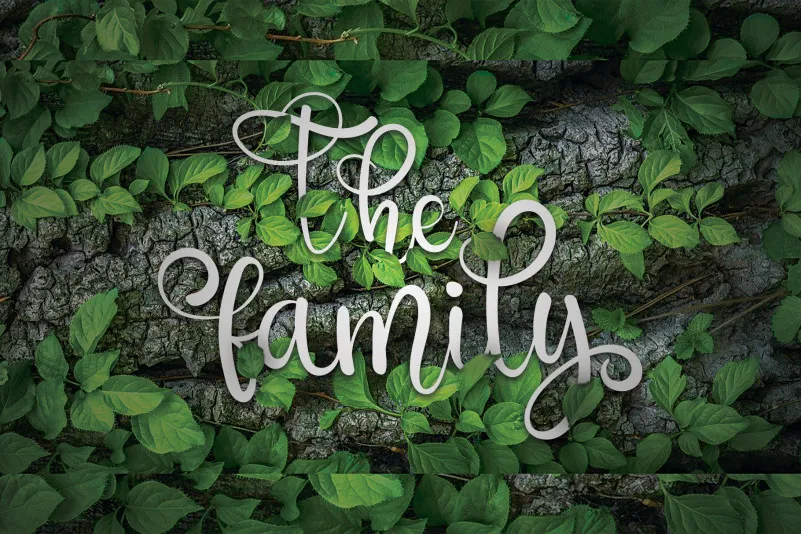
Esta fonte The Family Font é ideal para quem busca um toque romântico e encantador para seus projetos. Ela é uma tipografia de calligrafia que parece dançar ao longo da linha base, oferecendo um estilo casual e elegante aos seus designs. Cada letra possui um toque único e belo, tornando sua criação viva e vibrante. Seja para gráficos de newsletter, anúncios ou até mesmo em artes de decoração, The Family Font trará uma sensação especial a qualquer projeto. É perfeito para designers que buscam agregar um toque poético aos seus trabalhos. Não deixe de explorar a riqueza e a delicadeza desta fonte inspiradora.